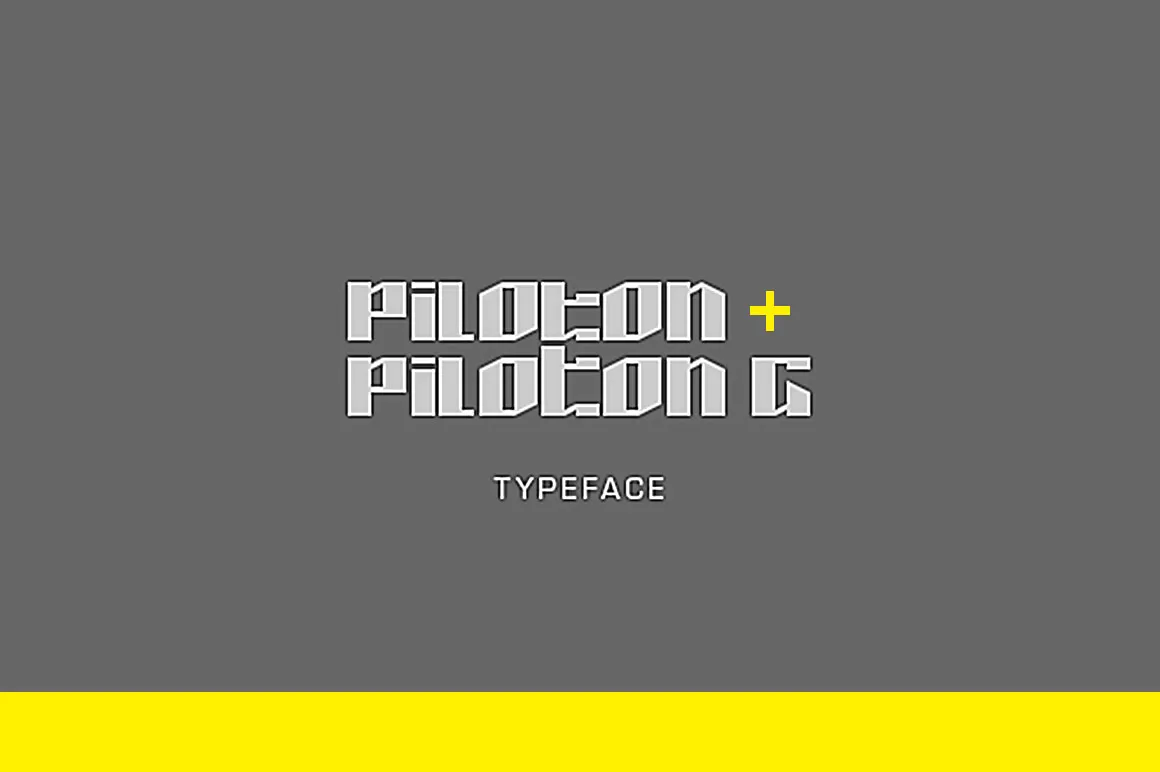
Piloton and Piloton G Free Fonts – Download Grátis
São duas lindas fontes customizadas que você certamente vai amar para seus novos projetos digitais. “Piloton” e “Piloton G” são criações incríveis do designer Aaron Amar, com um estilo moderno e futurista único. Elas se destacam não apenas por sua beleza visual, mas também pela versatilidade que oferecem para criar designs distintivos e inovadores. Com uma aparência elegante e clara, elas serão ótimas escolhas para textos em portfólio de design, logotipos ou qualquer outro conteúdo online onde você deseja usar um estilo chamativo. Descarregue estas fontes gratuitas e comece a experimentá-las hoje, garantindo que seu próximo projeto digital seja impecável!